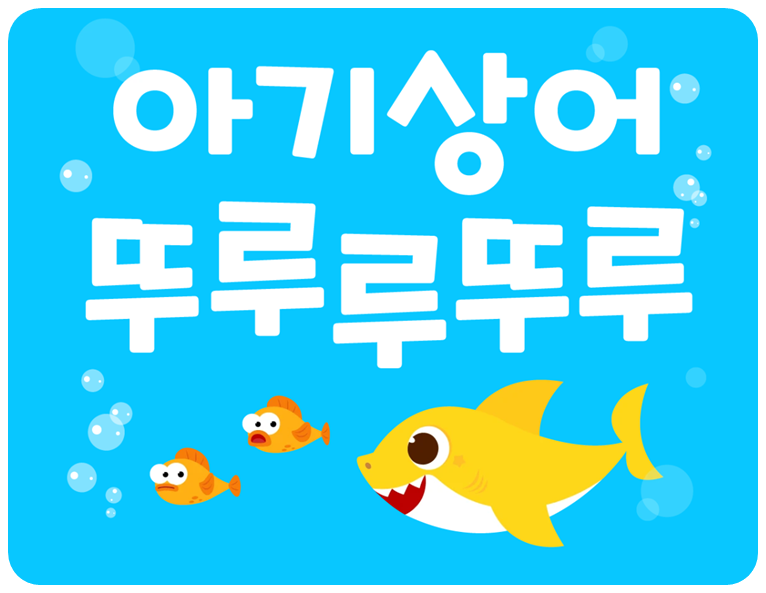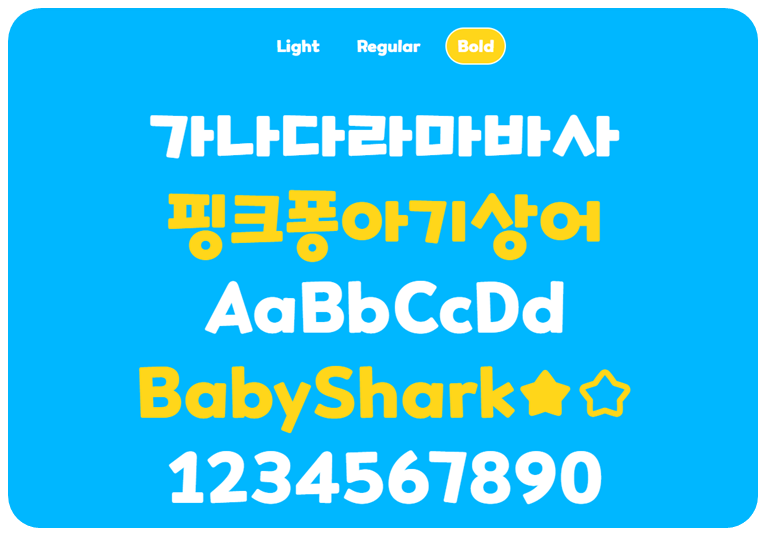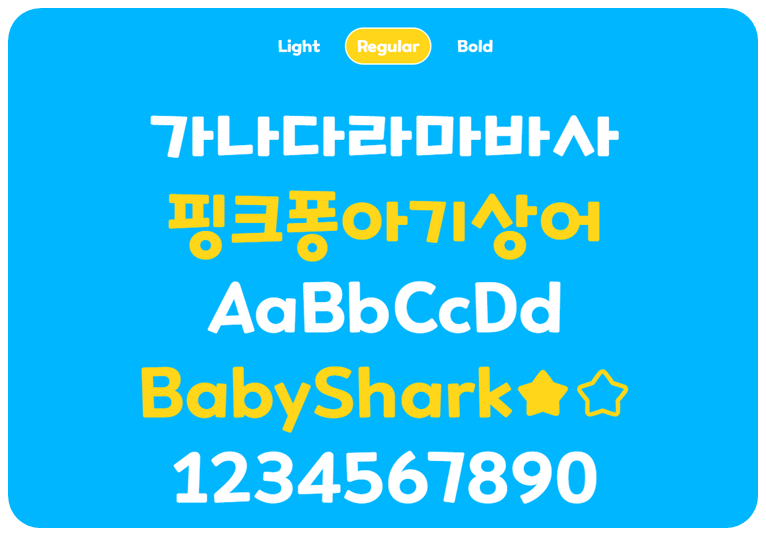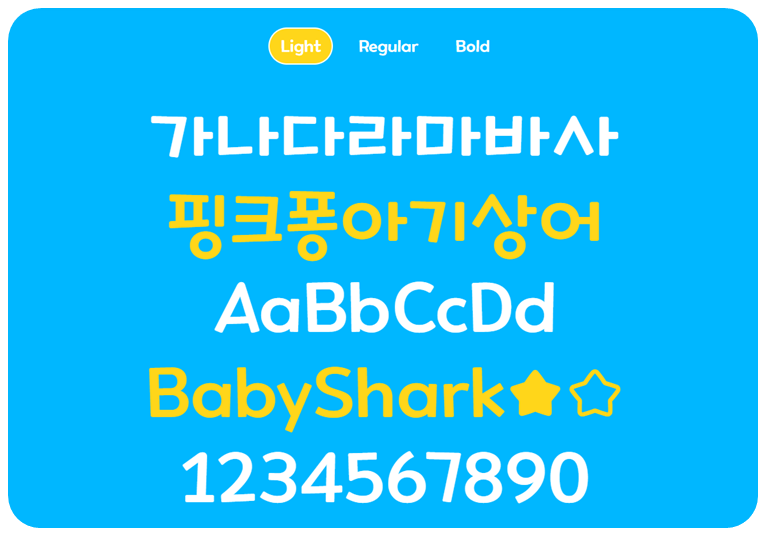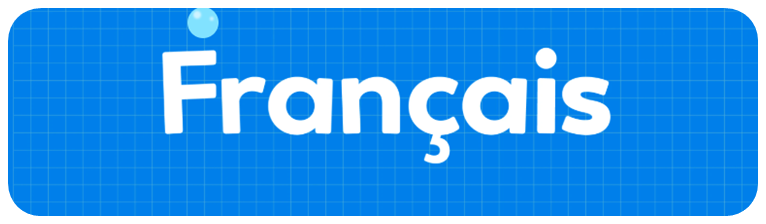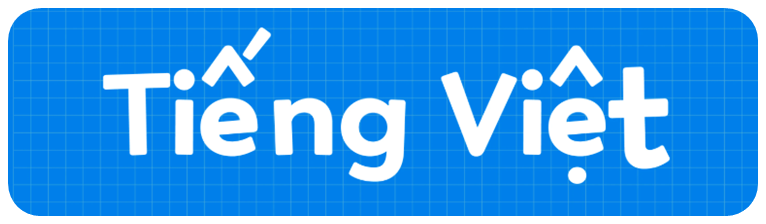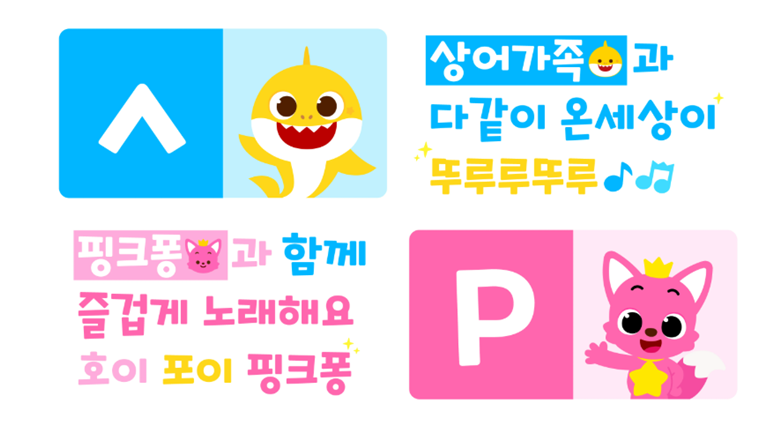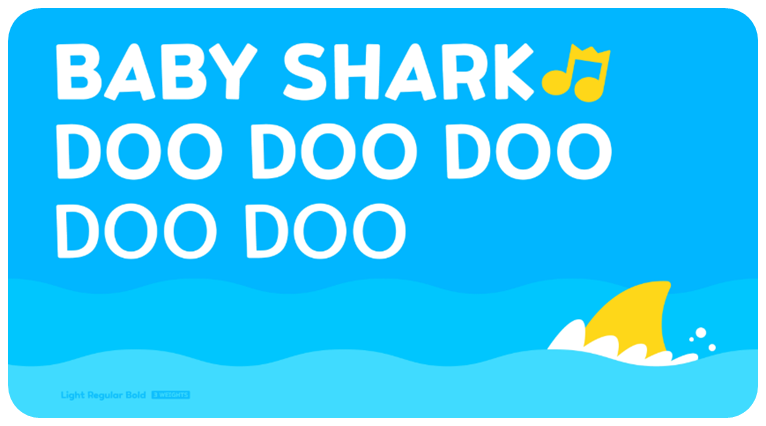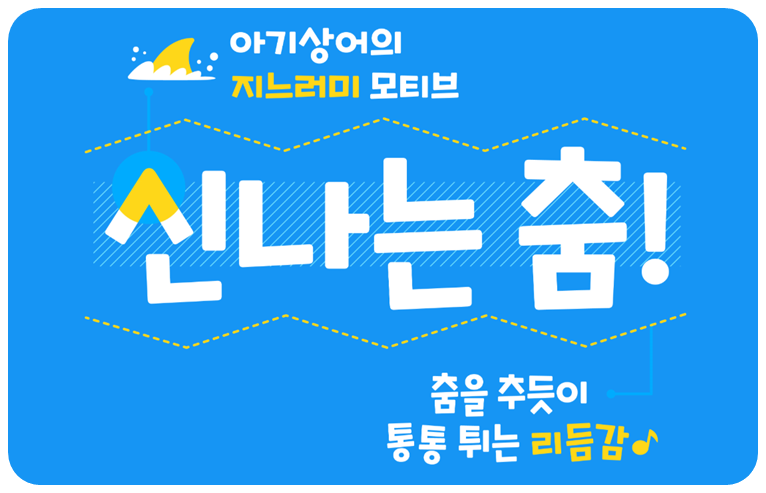
귀엽고 유쾌한 디자인, 그리고 글로벌 사랑을 받은 아기상어가 폰트로 찾아왔습니다. 10년간 전 세계를 사로잡은 '핑크퐁 아기상어'의 매력을 이제 글자에서도 느껴보세요. 지금 바로 무료로 다운로드해 사용할 수 있는 특별한 기회를 소개합니다.
핑크퐁 아기상어 폰트 특징
아기상어의 등지느러미에서 영감을 얻은 삼각형 모양의 대담한 디자인과, 경쾌한 리듬감이 살아있는 폰트입니다. 마치 "아기상어 뚜루루뚜루" 멜로디처럼, 글자 하나하나가 발랄하고 즐거운 분위기를 만들어줍니다.
다국어 지원과 문자 구성
이 폰트는 총 13,200자를 지원합니다.
- 한글: 11,172자
- 영어: 94자
- 라틴 문자: 952자
- 특수문자: 982자
지원 언어는 한국어, 영어, 스페인어, 포르투갈어, 프랑스어, 독일어, 이탈리아어, 베트남어, 인도네시아어 총 9개로, 글로벌 프로젝트에도 활용할 수 있습니다.
귀여운 아이콘 포함
핑크퐁 아기상어 별 아이콘을 비롯한 귀여운 심볼들이 포함되어 있어, 문서 작업, 카드 제작, 노트 작성 등 다양한 디자인 작업에 개성을 더할 수 있습니다.
핑크퐁 아기상어 폰트는 귀여움과 유쾌함, 그리고 글로벌 호환성을 갖춘 무료 폰트입니다. 특히 키즈 콘텐츠 제작자, 브랜딩 디자이너, 크리에이터라면 꼭 한번 활용해보세요. 무료 다운로드가 가능한 지금이 바로 최고의 기회입니다.